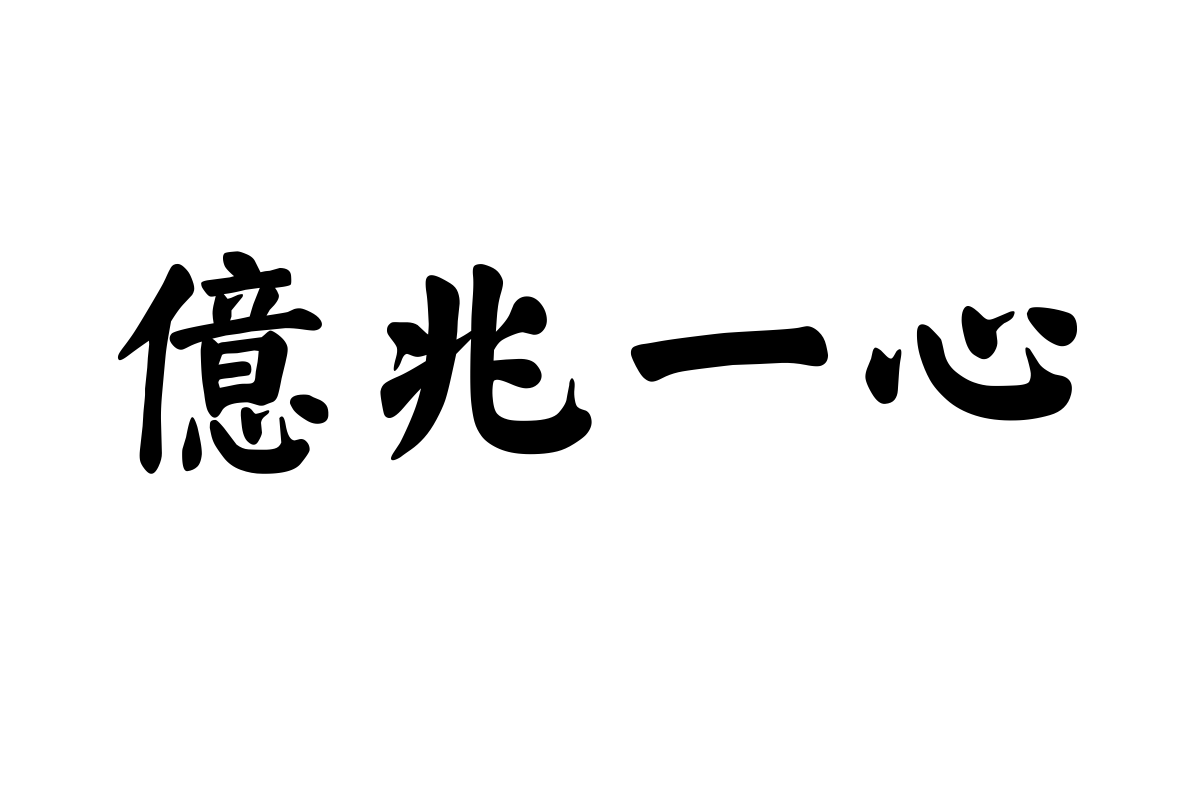
汉仪颜楷繁是一款由汉仪公司开发的字体,主要用于中文排版。这款字体具有以下特点:
1. 简洁明快:汉仪颜楷繁的笔画清晰,结构紧凑,给人一种简洁明快的感觉。
2. 易于阅读:这款字体的字形规整,笔画流畅,使得阅读起来更加轻松,提高了阅读体验。
3. 适用于多种场合:无论是用于书籍、报纸、杂志还是网页设计,汉仪颜楷繁都能很好地适应各种场合的需求。
总之,汉仪颜楷繁是一款适合各种应用场景的字体,具有简洁明快、易于阅读等特点,且支持免费商用,是设计师们常用的一款字体。